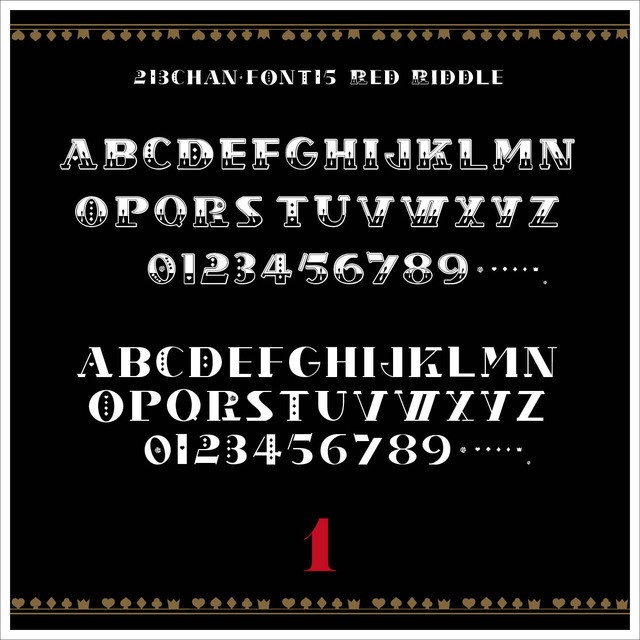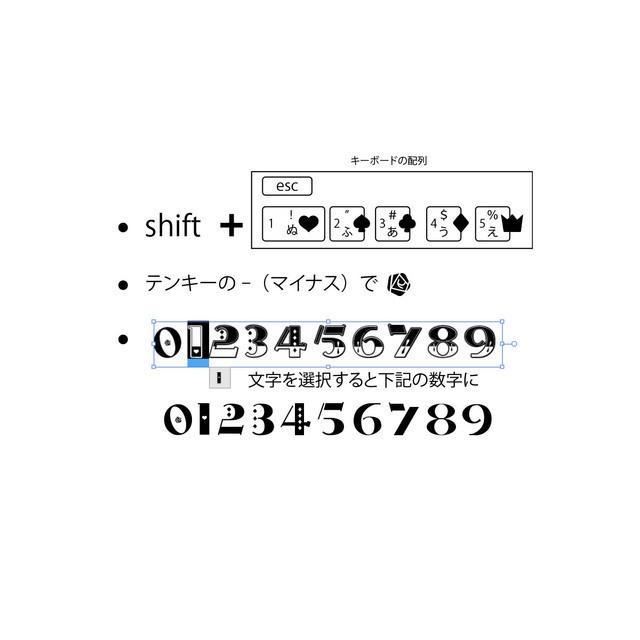
Red Riddle_font【商用可】
このRed Riddleフォントは213ちゃんが作った15個目 商用可のフリーフォント(freefont)です。 トランプ柄風のデコライティブな ディスプレイ書体です。 人気スマートフォンゲームのとある寮・・・ からインスパイアされたフォント第二弾になります。 あくまでも個人のイメージ、インスパイアなのでよろしくお願いします。 大文字はディスプレイ体、小文字はセリフ体 見た目はどちらも大文字です。 印刷物・ゲームやWeb、YouTubeのサムネイルやタイトルデザインなどにいかがでしょうか? 基本フリーですが、当フォントを利用した制作物などを、SNSで教えてくれると励みになります。 制作時のお気に入りポイントをnoteで記事にしています。 ぜひ遊びにきてね!スキ!お待ちしています。 https://note.com/sweet_2727/n/nc419e9b0d4d3 【収録内容】欧文(大小)・隠し文字 【Readme】フォントご使用上の注意 ・フォントの著作権は、213ちゃんに帰属します。 ・可愛がってくださるとうれしいです。 ・無断転載・再配布は堅くお断りいたします。 ・DLしたフォントに起因する損害は補償致しかねますので予めご了承ください。 ・使用する際の不明点はお問い合わせ先にご連絡ください。答えられる範囲でお返事いたします。 This font (213chan font) is a free OpenType font that can be used for commercial and personal web and print designs. Please take care of me. Font copyright belongs to 213chan. Unauthorized reproduction, redistribution, resale, and trademark registration of logos created using fonts is strictly prohibited. Please note that we cannot compensate for damage caused by DL fonts. Please note that we do not provide support regarding installation or usage.